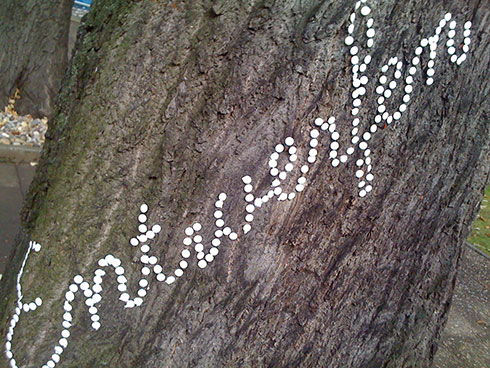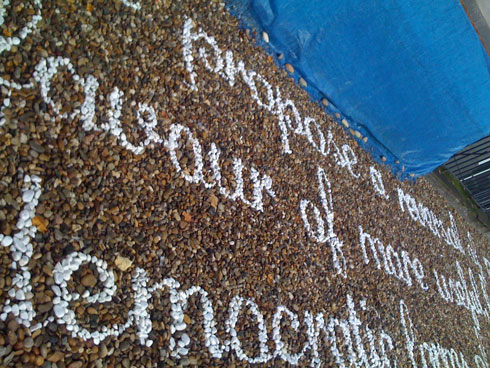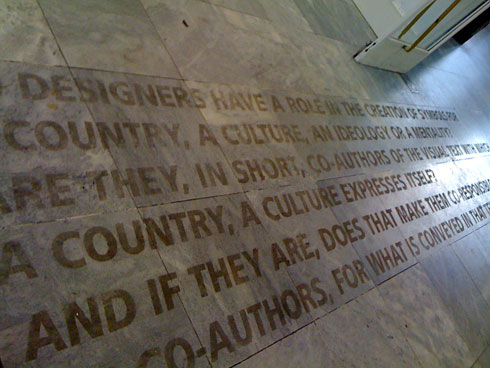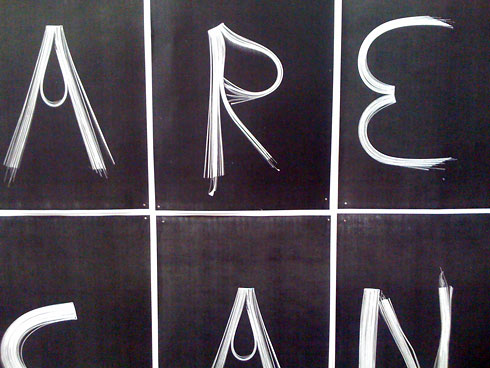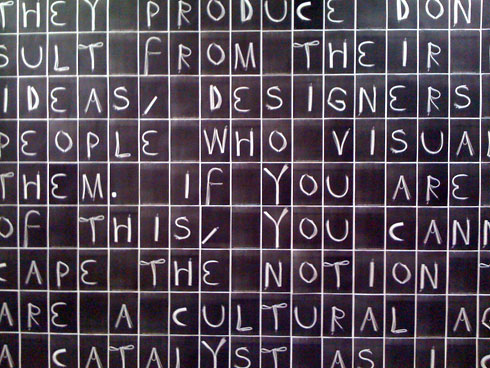
Auf dem Weg zum Saal begegne ich verschiedenen typografischen Installationen, von denen ich einige zeigen möchte. Oben ist eine Fotowand abgebildet (klicken, um Ausschnitt zu sehen), auf der Buchstaben aus verbogenen (Zeit-)Schriften zu sehen sind.
Diese klebrige Inschrift wurde erst am zweiten Tag richtig sichtbar, nachdem die Besucher hundertfach darüber gelaufen sind.
Sagmeisteresk 1: Reißzwecken in Baumrinde
Sagmeisteresk 2: Wörter im Kiesbett
Meine Sicht auf die Dinge … der Saal füllt sich langsam
Lars Müller, ist 1955 in Oslo geboren, der Norweger lebt seit 1963 in der Schweiz. Nach einer Berufslehre als Grafiker und Lehr- und Wanderjahren in den USA und Holland eröffnete er 1982 sein Atelier in Baden (Schweiz). Seit 1996 ist er Partner der interdisziplinären Designgruppe Integral Concept, die in Paris, Mailand und Baden wirkt. 1983 begann Lars Müller seine Arbeit als Verleger von Büchern zu Typografie, Design, Kunst, Fotografie und Architektur. Seit 1985 lehrt er regelmäßig an verschiedenen Hochschulen. Lars Müller ist Mitglied der Alliance Graphique Internationale.
Der Verlag stellt sein Programm als »Schule des Sehens« vor, als präzise Auswahl aus der unüberschaubaren Flut visueller Ereignisse und versammelt Autoren, Gestalter und Künstler, die Ihrerseits für Qualität und Auseinandersetzung einstehen: Josef Müller-Brockmann, Edgar Reinhard, Jasper Morrison, Peter Zumthor, Thomas Flechtner.
Thema seines Vortrags: »Der Autor als Gestalter«, also er dreht das Thema der Veranstaltung einfach um. Müller spricht deutsch mit Schweizer Akzent. Er fragt das Publikum »Wie politisch fühlen Sie sich heute?« »Werden Sie die gleiche Partei wieder wählen?« Müller glaubt, dass Autorenschaft eine politische Meinung voraussetzt. Das muss nicht militant sein. Müllers politische Initialisierung waren Aktionen in der Schweizer Anti-Atomkraftbewegung. Auch Müllers Lehrer und Vorbilder waren stets politische Autoren: Richard Paul Lohse, Josef Müller Brockmann, Richard Buckminster Fuller und Le Corbusier, der 39 Bücher geschrieben und selbst gestaltet hat.
»Ich bin, wie die Amerikaner sagen, ›the analog guy‹ – der mit dem Buch.« Zwischenfrage von Lars Müller »Warum, zum Teufel, wollen alle Bücher gestalten?« Das Buch ist eine körperbezogene Sache (er zeigt ein Buch, auf dessen Titel schlicht »2 Kilo« steht). Das sei der falsche Ansatz. Sein erstes Buch »Die gute Form« war eher bescheiden angelegt. Es handelte vom Design in der Schweiz der 50er und 60er Jahre, ein Selbstauftrag. Er arbeitete sich mittels Bücher in Inhalte hinein. Sein nächste »Opfer« war El Lissitzky.
Sein Verlagsprogramm spiegelt immer auch seine persönlichen Interessen wider. Bücher können zu Freundschaften führen und umgekehrt: das kann ein Mench sein (Ruedi Baur) oder eine Schrift (Helvetica).
Vergangenen Dienstag wurde Stefan Sagmeister in Berlin der hochdotierte Lucky Strike Design Award verliehen (Fontblog Twitpic 1 und Twitpic 2). In seiner Dankesrede erzählte er dem Publikum Geschichten aus dem Sabbatical auf Bali. Alle sieben Jahre gönnt sich Sagmeister eine Auszeit, in der keine Aufträge angenommen werden sondern zweckfrei neue Ideen entwickelt. Im Saal war Neid spürbar, als er von den freilaufenden Hunden auf Bali erzählte, die ihn zu Möbeln und einer T-Shirt-Serie inspirierten, als er Bilder von seinem Haus mit großer Terrasse zeigte und erzählte, er habe sich in dieser Zeit mit dem Thema Glück beschäftigt.
Stefan Sagmeister, wurde 1962 in Bregenz in Österreich geboren, studierte Grafik und Design an der Universität für angewandte Kunst Wien und am Pratt Institute, New York. 1993 gründete er dort sein eigenes Büro. Seiner Passion für Musik drückte sich er mit CD-Cover-Designs und Packaging für namhafte Interpreten aus. Sagmeister erhielt für seine Arbeiten zahlreiche internationale Auszeichnungen, darunter einen Grammy für ein Albumdesign der Talking Heads. Er unterrichtet an zahlreichen Hochschulen, u. a. an der School of Visual Art sowie an der Cooper Union School of Art in New York.
Stellt zunächst seine Arbeit für das David Byrne/Brian Eno-Album »Everything That Happens Will Happen Today«. Danach die Konzepte für den politisch-sozialen Verein True Majority, der 15 % des US-Rüstungsetats für soziale Zwecke abzwacken will (das wären rund 85 Mrd. Dollar). Dann erzählt er von seinem 2. arbeitsfreien Jahr nach 2000.
Einige Zitate:
Der neue Masterstudiengang Gutenberg-Intermedia der FH Mainz beginnt im nächsten Herbst.
Warum das Thema Autorschaft im Design? Es geht um Themen und Projekte, bei denen sich Designer intensiv den Inhalte ihrer Arbeit widmen. Genau dann entstehen spannende Arbeiten. Stichwort: Glaubwürdigkeit.
Wann wird ein Designer Autor? Gute Frage, in einer Zeit, in der sich die Autorschaft eher aufzulösen scheint: Soziale Netze, Crowd-Sourcing, Creative Commons, …
Dr. Petra Eisele, studierte Kunstgeschichte, Literaturwissenschaft und Linguistik in Trier und promovierte anschließend an der UdK in Berlin. Sie war Mitarbeiterin an der Bauhaus-Universität Weimar und versteht sich als Designforscherin. Heute ist sie Prof. für Designgeschichte, Designtheorie und Medientheorie in Mainz. 2008 gründete sie mit Forschern die Gesellschaft für Designgeschichte (GfDg). Im Fokus ihres Interesses stehen aktuelle Entwicklungen im Produkt- und Kommunikationsdesign, insbesondere Organic Design, Konvergentes Design, DDR-Design und Rezeptionsästhetik.
Gestern: Verschlüsselte Autorschaft des Designers, industrieorientiert, Massenproduktion. Der Gestalter tritt hinter den Produkten zurück, dient der Produktion. Beispiele: Chanel (Nº 5) und Braun (»Geräte sollen stumme Diener sein«). Designer sollten hinter den Produkten verschwinden, auch die Produkte selbst sollten nicht auffallen.